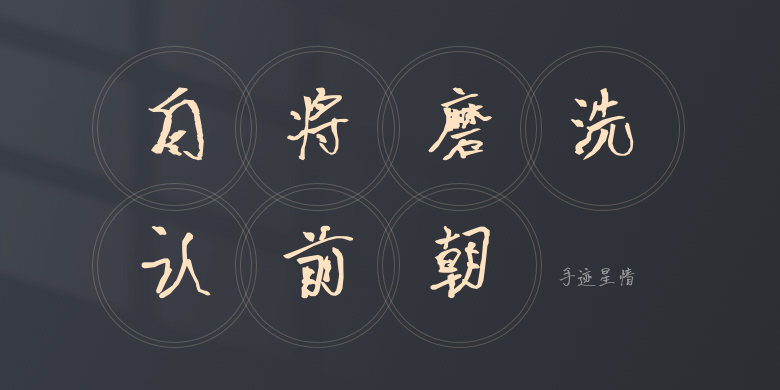
手迹星情
手迹星情,这款字体结构工整、笔画清晰,兼顾美观与易读性,适用于标题、正文、海报、包装、LOGO 等多种场景。字形优雅稳定,风格百搭耐看,适配日常排版与创意设计,让文字呈现更舒适、更具质感。手迹星情一笔一画,皆是细节,以均衡的比例、流畅的线条打造舒适视觉体验,字形端正大气,风格简约现代。无论是商业设计、品牌宣传还是日常排版,都能轻松驾驭,让文字更有格调与力量。手迹星情字体下载。